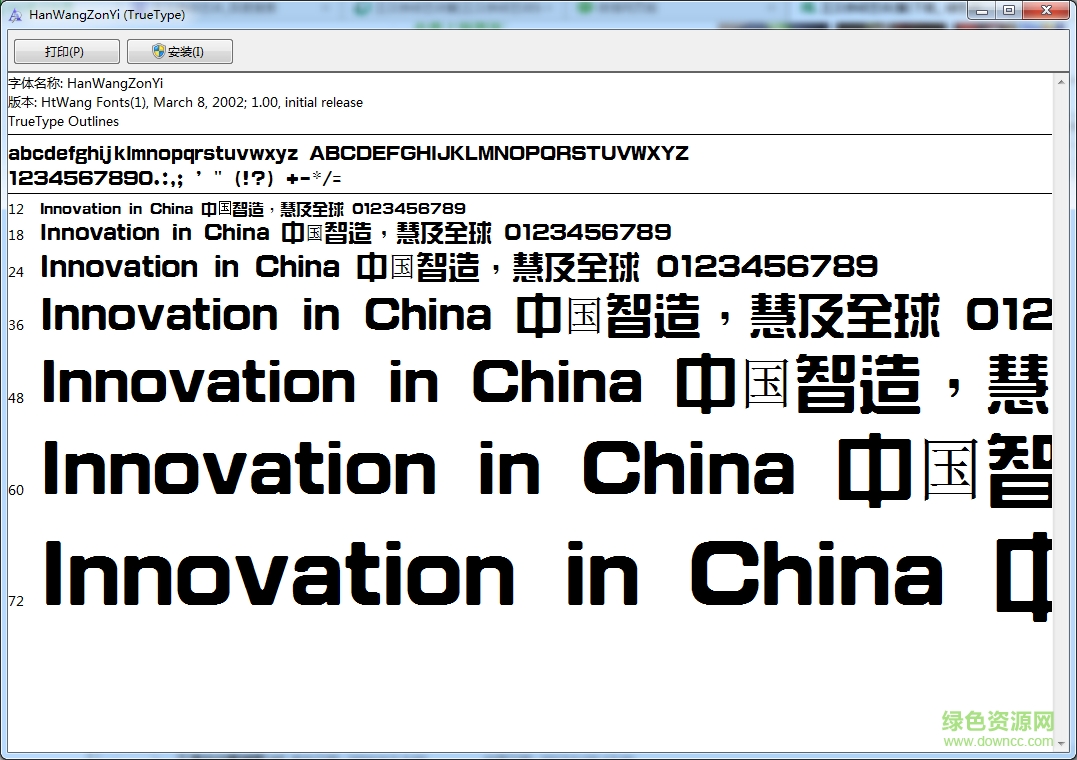
王汉宗综艺体
王汉宗综艺体是一款应用领域非常广泛的电脑字体软件,文字粗细错落,非常的独特和醒目,字体端庄大气使用便捷独具美感。喜爱的朋友快来绿色资源网下载体验吧!
王汉宗综艺体是一款专门用于美工设计方面的电脑字体,改字体潇洒俊逸、自然舒展,让人赏心悦目,整体效果非常的统一,而且字库完整,喜欢的用户可以来体验。